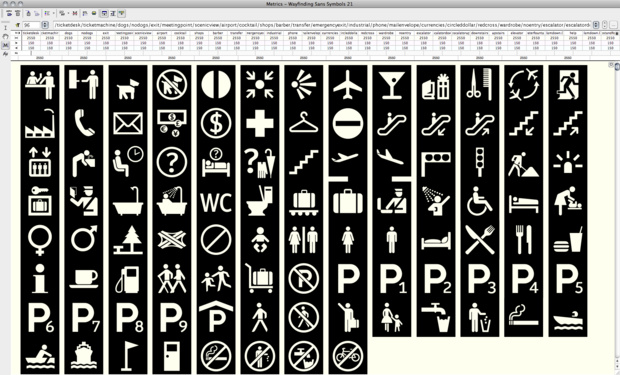
Nur am Rande bemerkt, falls du daraus ein Schild produzieren lassen möchtest: es wäre nicht notwendig, das auszuschneiden. Die Folien sind opak genug, dass das nicht durchscheint, wenn du die komplette Figur darunter hast. Beim ausgeschnittenen Motiv hast du vielmehr das Problem der Passerungenauigkeit, da das ja von Hand zusammengesetz wird.
Äh, ja, ich dachte bisher nur an Freiflächen, nicht an Parkdecks. Aber gute Idee.
Man sieht aber auch nicht alles in dem Bild. Ich werd zu gegebenen Zeit nochmal alles Piktogramme zeigen. Dann nehm ich sehr gern noch Feedback zu fehlenden Zeichen entgegen.
Ich wollte noch den fehlenden Feuerlöscher anmerken, aber wenn das eh nicht alle sind … bin gespannt auf das Ergebnis!
Gibt es eigentlich irgendeinen Grund, warum es keine einheitliche Bewegungsrichtung gibt? Also nicht nur in deinem Screenshot, sondern in vielen Icon-Sets. Der Fußgänger geht nach links, der Flüchtende nach rechts. Rolltreppen gehen nach rechts (oben), Mutter und Kind nach links …
Mal eine reine Vermutung: Ist es nicht so, dass alle Personen auf Schildern, die für Autofahrer gedacht sind, sich von rechts nach links bewegen, weil der rechte Bürgersteig dichter am fahrenden Auto ist als der linke und die Personen, die von dort kommen, gefährdeter sind, unter die Räder zu kommen, als die von links?
Bei allen anderen Dingen wie Rolltreppen und Notausgängen werden die Fußgänger dann aber als »Rechtsverkehr« behandelt, bewegen sich also von links nach rechts …? Wie gesagt, nur eine Vermutung. :-)
Ich müsste direkt mal prüfen, wie das hier in Südafrika gehandhabt wird – hier herrscht ja Linksverkehr.
Noch ein Gedanke zum Parkplatz: In M beispielsweise gehen die Nummern bis 81, mit Zusätzen Nord und Süd … kann man solche Anforderungen in Icons lösen?
Das könnte eine Erklärung sein. :-) Müssten sich dann die Personen in den Icons (die ja nicht als Verkehrschild gedacht sind) konsequenterweise alle nach rechts bewegen? Oder sind die Bewegungsrichtungen "gelernt" und werden schneller erkannt wenn sie wie im Straßenverkehr sind?
Hmmm, da Ralf seine Schrift ja speziell für den Einsatz in Verkehrssituationen entwickelt, lässt es sich nicht ausschließen, dass die Piktogramme dann auch in entsprechendem Kontext (oder Publikationen dazu) eingesetzt werden. Daher würde ich die gelernten Richtungen beibehalten, wenn denn solch ein Sinn dahinter steckt.
Das würde wahrscheinlich mehr Schaden als Nutzen bringen, weil man dann zugunsten einer richtungsneutralen Gestaltung die Erkennbar unnötig verschlechtern würde. Es ist ja auch nicht so, dass die Leserichtung ein dominierendes Element wäre. Prinzipiell steht die Erkennung der Sache im Vordergrund. Auch bei verkehrter Leserichtung sollten die Piktogramme eindeutig sein. Deshalb haben die Dinge wie Treppen eindeutige Pfeile und verlassen sich natürlich nicht nur auf die Interpretation über die Leserichtung.